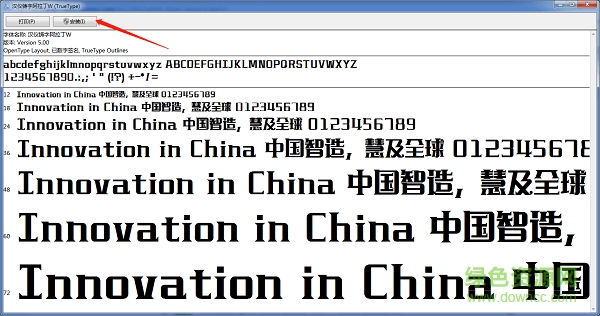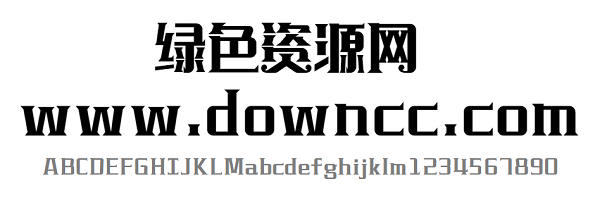
漢儀鑄字阿拉丁w,帶你體驗(yàn)阿拉丁神燈的傳奇,這款字體的畫風(fēng)在設(shè)計(jì)上融入了奇幻的阿拉丁素材,字體的收筆之處都有一個(gè)轉(zhuǎn)換,讓字體整體看起來非常具有特色,不過此款字體只適用于標(biāo)題,需要的用戶就來綠色資源網(wǎng)下載吧!
漢儀鑄字阿拉丁W字體是一款不錯(cuò)的中文字體,這款字體筆觸較為粗實(shí),字體清晰大氣,有點(diǎn)兒像一款具有自己特色風(fēng)格的藝術(shù)字體,動(dòng)畫特色的融入又讓字體添加了一份神秘!
字體家族:漢儀鑄字阿拉丁